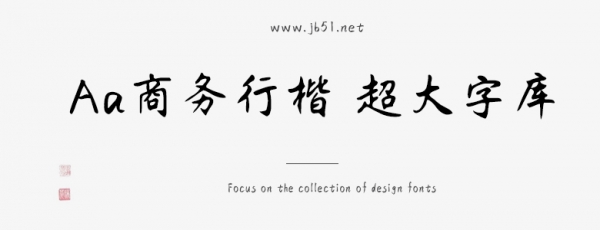
Aa商務(wù)行楷 超大字庫是一款不錯(cuò)的藝術(shù)字體,由Aa字庫出品,字體筆觸適中,字形端正 ,具有很好的視覺感,適合應(yīng)用于藝術(shù)設(shè)計(jì)、平面宣傳設(shè)計(jì)、網(wǎng)頁設(shè)計(jì),書法字帖等領(lǐng)域,需要的朋友可以前來本站下載。